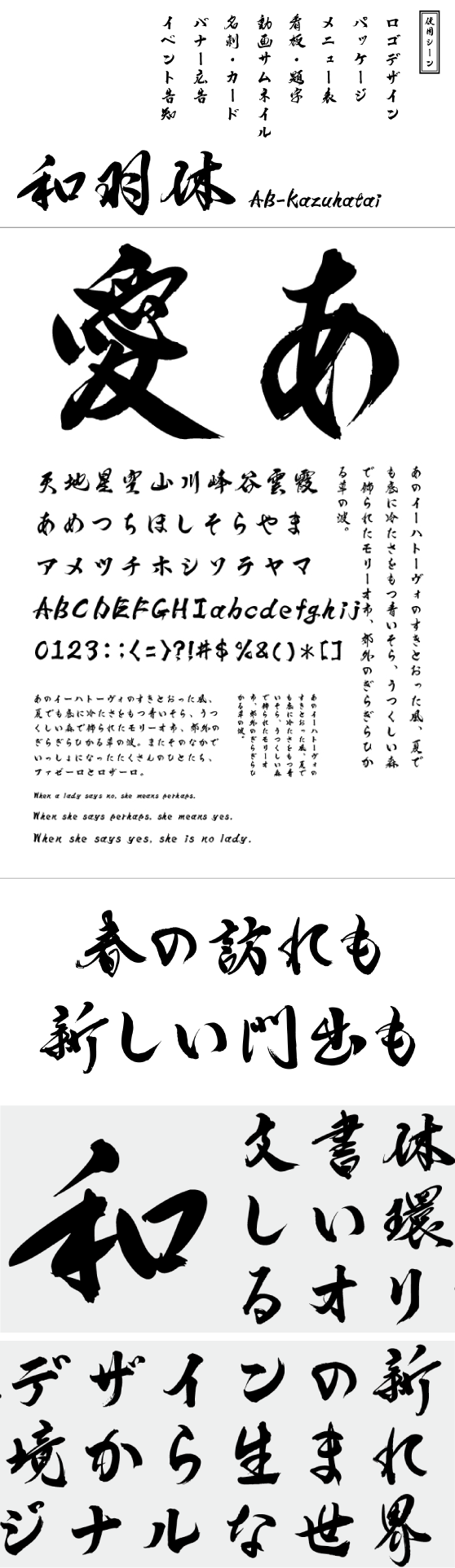
デザイン毛筆
ウェブフォントジャパン株式会社
手書き屋本舗 TAw-和羽体 J1 Regular (Kazuha)
TAw-kazuhataiJ1-Regular
筆圧の強弱や運筆のスピードをそのまま線に表し、全体に流れるような表情をもつ書体です。一画一画に抑揚があり、軽やかな動きとリズムで表現しました。やわらかさの中に芯のある力強さも感じられ、上品さと親しみやすさを兼ね備えているため、作品制作から実用的なデザインまで、さまざまなシーンで幅広くご使用いただけます。
JIS第一水準(2,965文字)までを収録・ひらがな・カタカナ・アルファベット・数字・記号